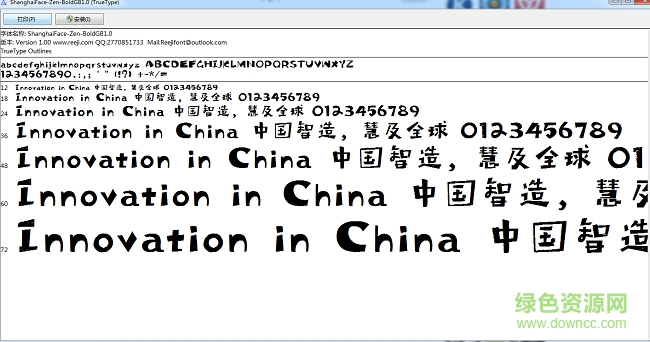
shanghaiface zen boldgb1.0字體是一款由銳字工房推出的海派腔調(diào)禪粗黑簡(jiǎn)1.0字體,筆畫干凈利索,黑白對(duì)比強(qiáng)烈,腔調(diào)十足,極具美感,歡迎喜歡的朋友免費(fèi)下載使用!
海派腔調(diào)禪粗黑1.0是在海派腔調(diào)藝術(shù)黑的基礎(chǔ)上,進(jìn)一步減小筆畫的粗細(xì)對(duì)比性,在進(jìn)一步增強(qiáng)通用性的基礎(chǔ)上保留了原有的結(jié)構(gòu)的狀態(tài)。
字體采用疏松的結(jié)構(gòu),整個(gè)字形的通透性很強(qiáng),使人看后心情放松愉悅;與傳統(tǒng)字相反的疏密處理方法,增加了每個(gè)字的趣味性;筆畫中的小點(diǎn)減輕了復(fù)雜筆畫的重量,使字態(tài)輕盈;筆畫雖散,但結(jié)構(gòu)緊湊,整個(gè)字形散神不散。